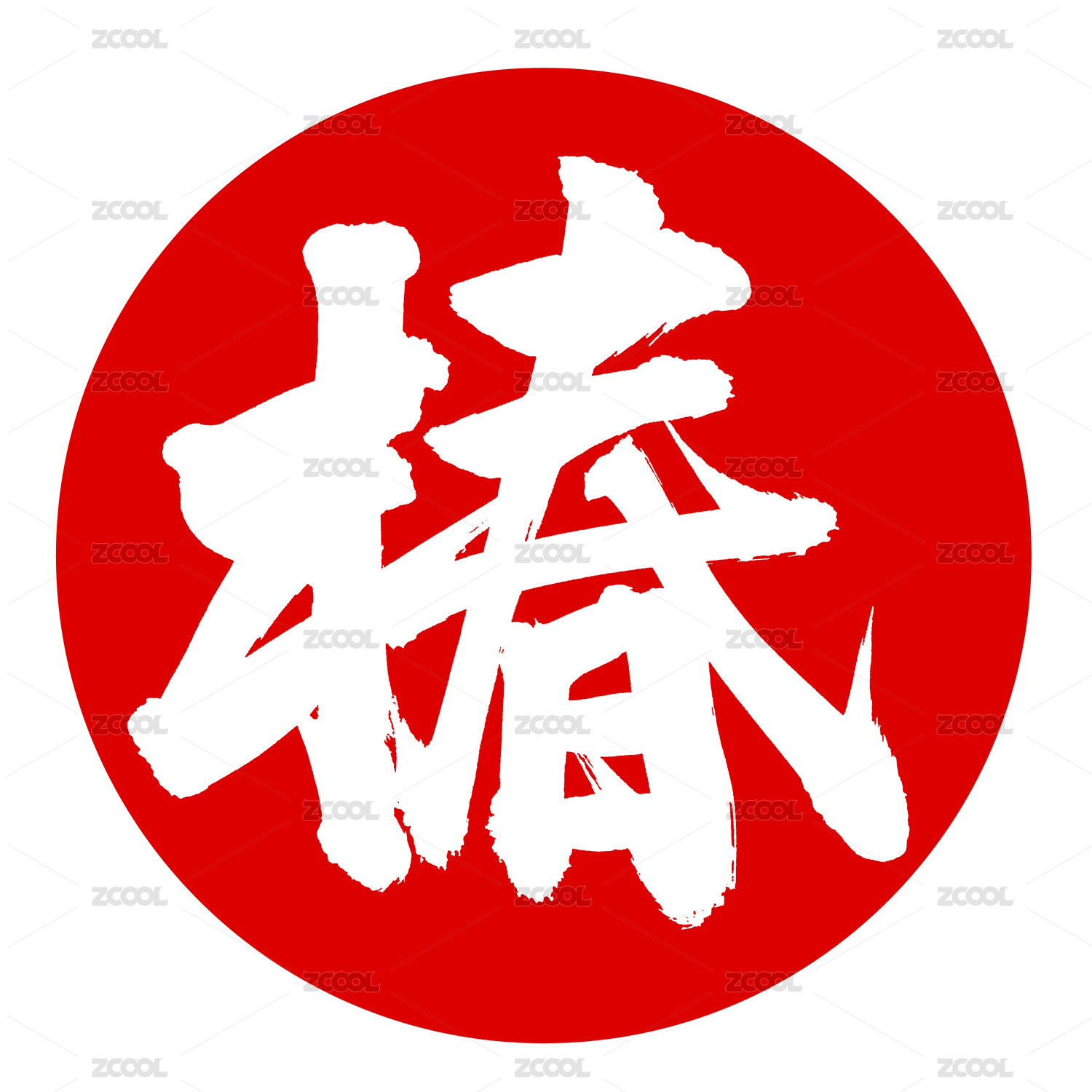
字由人生
字由人生-歌名系列
今年整整毕业三年
三年不长不短
但也发生了很多事情
唯一没变的就是
自己仍然在坚持做设计
有时候感情无法宣泄
也只能通过音乐和设计来表达吧
记得曾经有人说过:带上耳机你就拥有了全世界
这些设计每一个我都尽力表达歌所传达给我的感受吧
做了很多商业设计 这次也算为自己设计一次
杨宗纬 实力唱将 比原唱好听 不接受反驳
小鬼 比较带感的歌 推荐
往后余生是你 你看到“你”了么
王北车的陷阱 据说抖音火起来的 但是我不玩抖音~一个小心心掉入陷阱
即使一粒尘土 我也要满天飞舞
不解释 很好听
人尽皆知的歌吧 超时空同居 主题曲
做设计的路上一定会有嘲笑和异议 借用灰昼大神的话 唯有热爱可以抵御漫长岁月 共勉
节奏轻快的钢琴独奏 不听后悔
这个设计 中间是两个人在接吻的侧脸,比较抽象~
纠结 没办法 设计师都有强迫症 不得不纠结
买辣椒也用券 这人肯定爱吃辣 湖蓝人
许嵩 的 还可以吧
既然活着 就好好过
空空空空如也!
挺现实的歌 小眼男神李荣浩
逝去的才是人生 自己悟吧
分开的时候 还是要体面一点 做人留一线 日后好相见
大师 久石让 的曲子 比较伤感
民谣活的一塌糊涂的赵雷 确实很棒这个 画一个姑娘~
fuck 只是一个语气词
贴了几个海报效果图~~
不用数了,凑个整20个,觉得不好的,可以打我,OK就这样